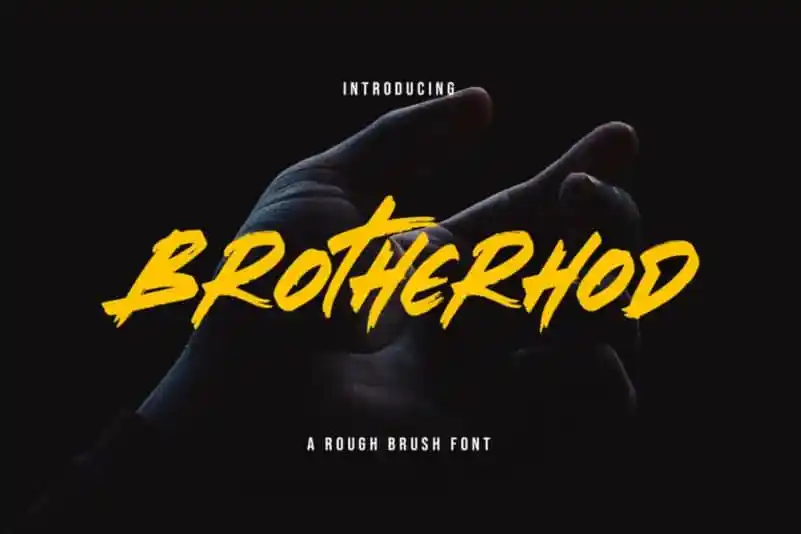
Brotherhod Brush Font – Fonte Grátis
Brotherhod Brush Font
A Brotherhod Brush Font é uma criação meticulosa do designer Rometheme para a categoria de Fonts Script, com um toque de efeito de raspagem que adiciona movimento natural. Este novo design apresenta um estilo elegante e sofisticado, fazendo-o perfeitamente legível e apelativo ao mesmo tempo. Além disso, oferece uma facilidade inigualável para a utilização, tornando-a ideal tanto para designers profissionais quanto para aqueles que desejam adicionar um toque único às suas criações digitais. Com seu design refinado e sua capacidade de se adaptar bem a vários usos, a Brotherhod Brush Font é uma escolha perfeita para quem procura uma fonte elegante e versátil no formato de scripts brushy.